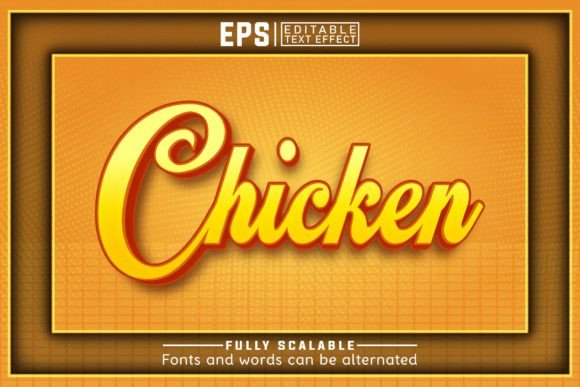
Chicken 3d -Editable Text Effect
Att hitta rätt designelement kan vara utmanande, men Chicken 3d -Editable Text Effect erbjuder en exceptionell samling som omedelbart lyfter ditt arbete.